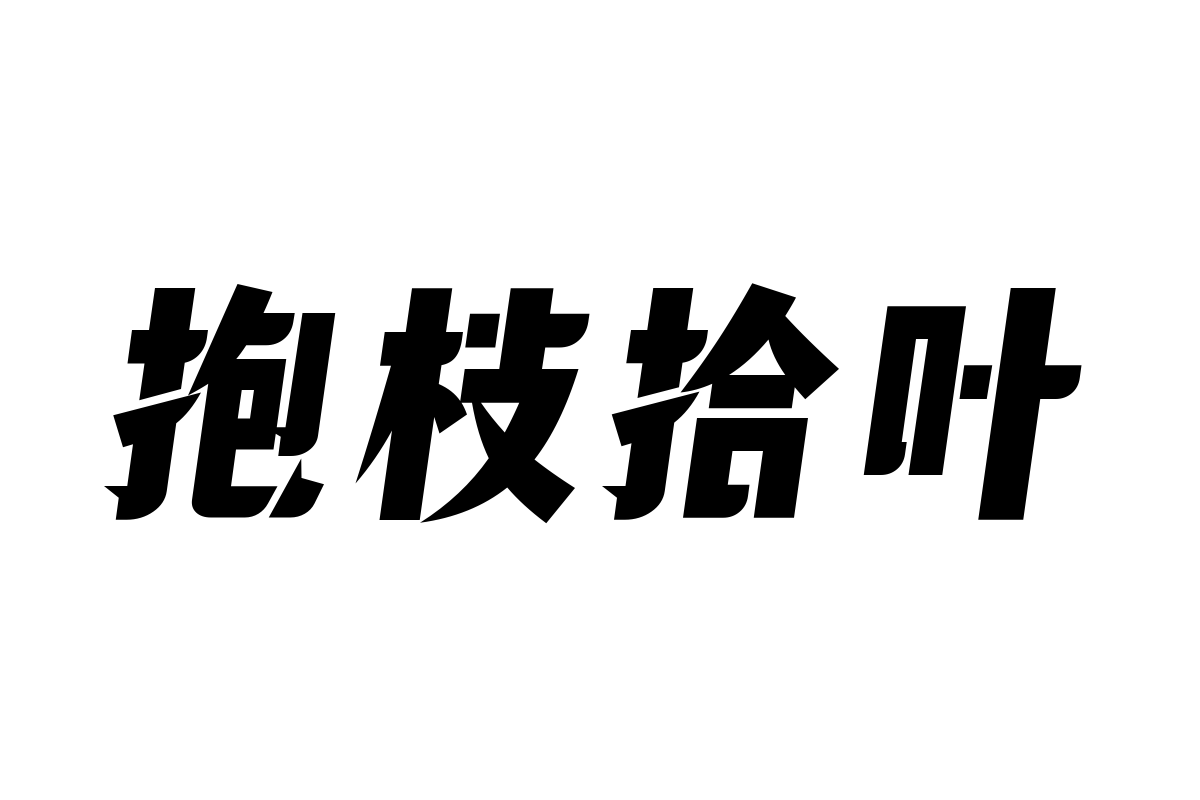
锐字奥运精神夺冠简体字体是一种具有独特设计元素的中文字体。该字体以简洁明了的线条和结构为基础,通过巧妙的组合和排列,展现出一种力量感和动感。这种字体适合用于各种需要强调速度、力量和竞技精神的场合,如体育赛事、广告宣传等。
锐字奥运精神夺冠简体字体的特点包括:
1. 简洁明了:该字体以简洁的线条和结构为基础,没有过多的装饰元素,使得整体视觉效果更加清晰明了。
2. 力量感:通过巧妙的组合和排列,该字体展现出一种强烈的力量感,能够吸引观众的注意力并传达出积极向上的精神风貌。
3. 动感:该字体通过动态的笔画和结构变化,营造出一种动感十足的视觉效果,使整个字体更加生动有趣。
4. 适合多种场合:由于其独特的设计元素,锐字奥运精神夺冠简体字体适合用于各种需要强调速度、力量和竞技精神的场合,如体育赛事、广告宣传等。
总之,锐字奥运精神夺冠简体字体是一种具有独特魅力和表现力的中文字体,适用于各种需要强调速度、力量和竞技精神的场合。